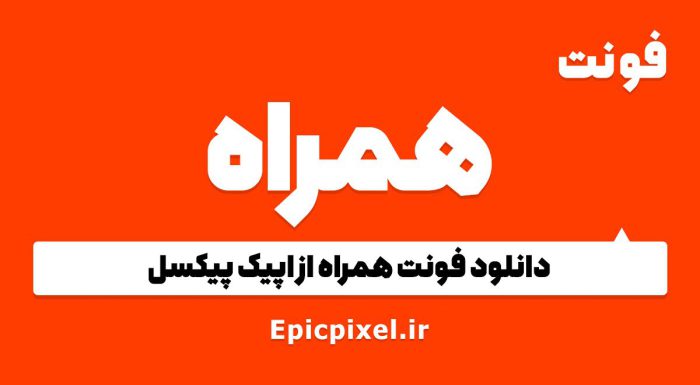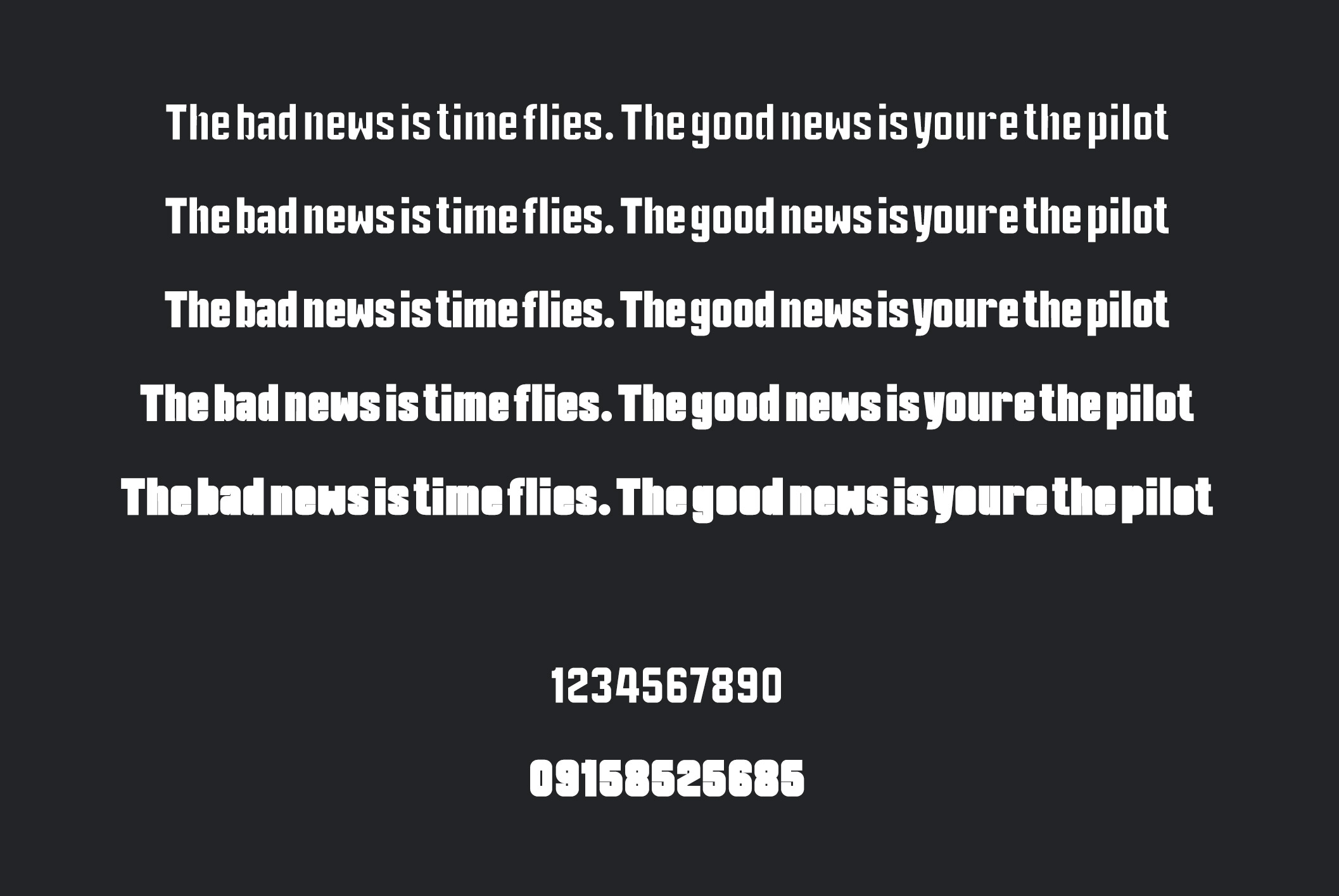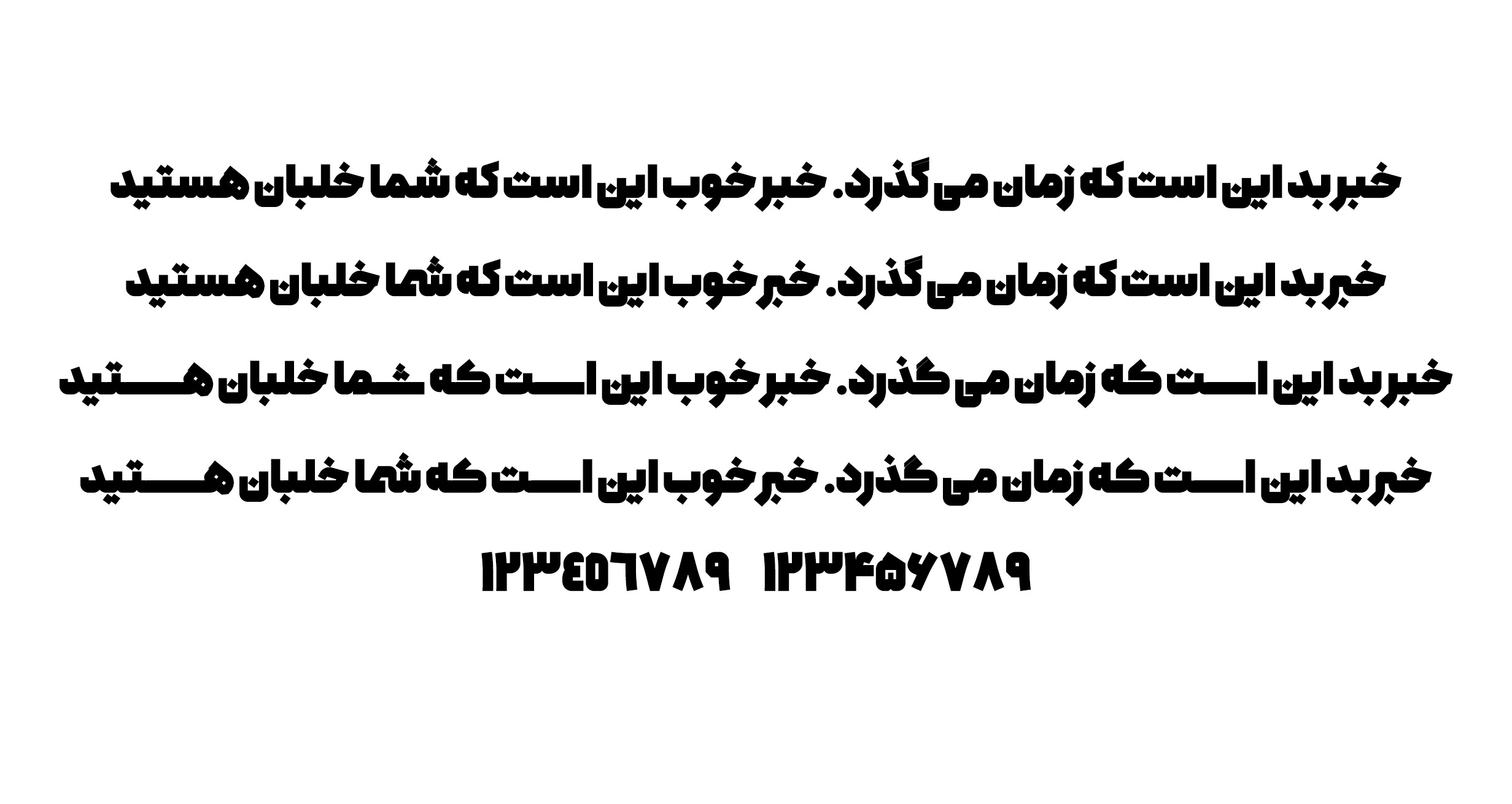
دانلود فونت Hamrah فارسی Font اپیک همراه |
| فونت | دانلود فونت فارسی اپیک همراه اکسترا لایت Font Epic Hamrah Extralight فونت همراه لایت Epic Hamrah Light همراه ریگولار Epic Hamrah Regular اپیک همراه مدیوم Epic Hamrah Medium بولد Epic Hamrah Bold |
| ⭐ توضیحات | مجموعه ای کامل از فونت های همراه و نسخه شبیه سازی شده اپیک همراه فونت اپیک همراه با پشتیبانی از حروف فارسی ، انگلیسی / لاتین ، اعداد فارسی Fu Num و نسخه وبسایت دارای چند استایل مختلف نوشتاری حروف |
فونت همراه از خط بنایی ساده الهام گرفته است، دارای استخوان بندی قوی و پایدار است و از خطوط راست تشکیل شده است.
این فونت از یک گرید رعایت می کند و حروف آن جدی و در عین حال مهربان به چشم می خورند
چشم ها کوچک شده و فضای سفید در داخل و بیرون حروف بسیار اندک است و حروف به خط کرسی نزدیک شده اند که باعث می شود که تأثیر و هماهنگی بالاتر شود.
نقاط ضعف و قوت در فونت همراه بسیار مجاور هم هستند. همه حروف به شکل ساده ای طراحی شده اند اما هر یک دارای شخصیت منحصر به فرد و جدیدی هستند. فونت همراه فقط یک وزن دارد و برای نوشتههای کوتاه مناسب است